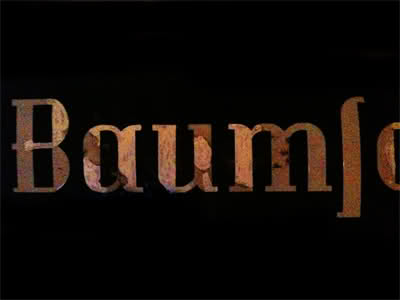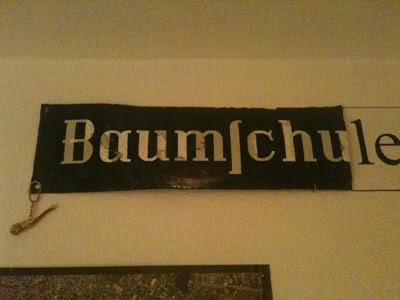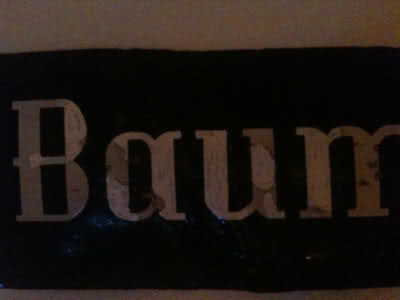
Suche Schrift von ca 80 - 100 Jahre altem Straßenschild
ich habe hier Bilder von einem Straßenschild aus Hamburg. Ich wüsste gerne welche Schrift das sein könnte? Bzw ob es diese denn überhaupt in der digitalen Welt gibt? Wer hat schon vor 80 Jahren an PC gedacht ;-)
Der Text auf dem gesamten Schilfd war "Baumschulenweg". Sorry das die Bilder nicht besser sind. Das Schild selber ist auch an einigen Buchstaben nachgemalt worden. Ausser das c sind aber alle in der original Form!
Das kleine "c" ist oben original, kann aber unten anders ausgesehen haben.
Markant an dieser Schrift ist sicherlich das große "B", das kleine "s", (das "c") sowie das kleine "a".
Ebenfalls ist mir aufgefallen das die Serifen am "h" zwar an beiden Füßen sind aber nur jeweils nach vorne und hinten, also nicht durchgehend oder so...
Hoffe mir kann jemand weiterhelfen, meinem Opa damit eine Freude zu machen, denn wir wollen das Schild nachmachen lassen.
Das ist ja wunderschön, sehr wahrscheinlich ist es aber nicht, daß man eine identische Schrift für den Rechner findet. Wenn es eine ordentliche Vorlage gibt und das Budget ausreicht, kann man das trotzdem nachbauen. Ehe man eine nur ähnliche Schrift nimmt, ist das sicher in dem Fall die bessere Lösung und der Aufwand ist überschaubar. Was soll denn am Ende das Ergebnis sein? Ein Emailleschild?
hast Du da mehr Buchstaben? Ich wollte mir bei Gelegenheit eine klassizistische Dekokacken-Antiqua basteln und habe deshalb mal probiert aus der Vorlage eine Schrift zusammenzunageln, aber ich bin nicht sehr weit gekommen. Mit ein paar weiteren Buchstaben könnte das im Laufe der Monaten noch was werden.
ne sorry mehr habe ich von dem schild leider nicht mehr!
die schrift wirst du wohl nicht als font finden, darum wäre es angebracht mit dem schild zu einem grafiker zu gehen und die fehlenden buchstaben nachbauen zu lassen. gute grafiker findest du auch hier im forum.
ich bin zwar kein Grafiker und auch nicht fähig, aber ich habe trotzdem mal angefangen. Allerdings habe ich einige Buchstaben geraten und diese sind anders ausgefallen als auf den Abbildungen. So ist das kleine t eine Zumutung und ich habe das ganze dekorativer mit Bommel unten zusammengebaut. Leider fehlen mir noch zuviele Buchstaben und ich wollte die Schrift in aller Ruhe zu Ende bauen.